J’ai commencé par m’approprier la méthode. Du coup, des premières semaines qui étaient très « flat » en terme de style. Je commence maintenant à passer à des choses plus graphiques. Malgré tout, cela reste un outil : priorité sur le contenu ! Mais autant mettre un peu de forme à moindre frais : cela aide encore plus à se l’approprier.
Des inspirations pour les mois dans mon Bujo
Voici quelques essais, pour réaliser les en-tête de l’agenda mensuel. Vous reconnaîtrez les reliques du stage Lettres et Fleurs dont je vous ai parlé la semaine dernière.
En partant d’une calligraphie simple, voir tout simplement de petites capitales, on peut imaginer des en-têtes sympas. Pour la calligraphie, j’ai opté pour la Candy Girl. Je vous donne ci-dessous un modèle d’écriture pour les mois, si vous souhaitez vous lancer.
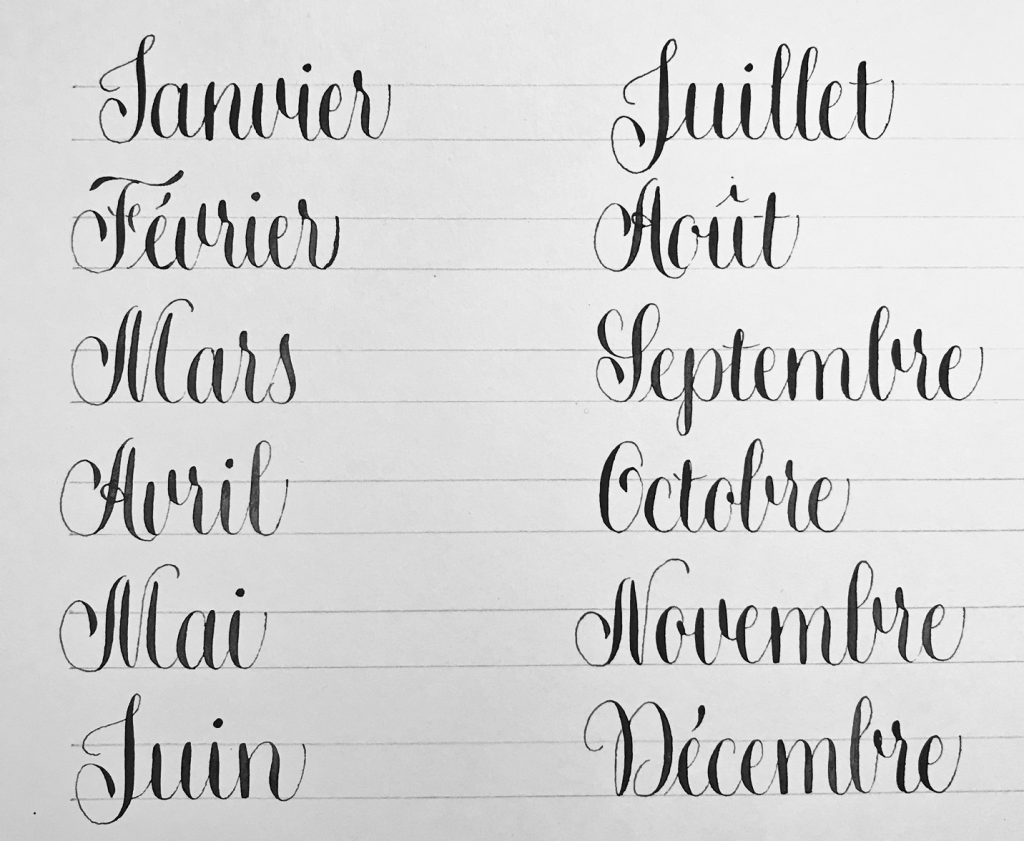
Peut-on écrire à la plume dans un Bujo ?
J’ai auparavant testé que l’écriture à la plume passait bien sur le papier de mon Bujo. En écrivant à la gouache, pas de souci : ça ne fuse pas et ne traverse pas les pages. J’ai un carnet Leuchturm, mais j’ai essayé aussi sur des carnets Hema ou Muji et je n’ai pas eu de problèmes.
Simplicité et sobriété
J’ai essayé de travailler sur quelque chose de simple, épuré, graphique, féminin et rapide à faire.
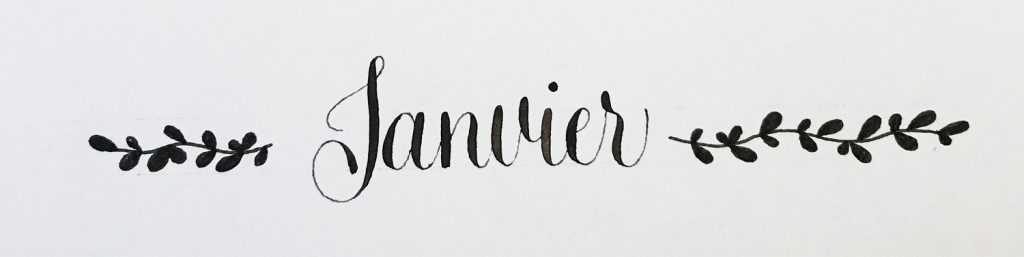
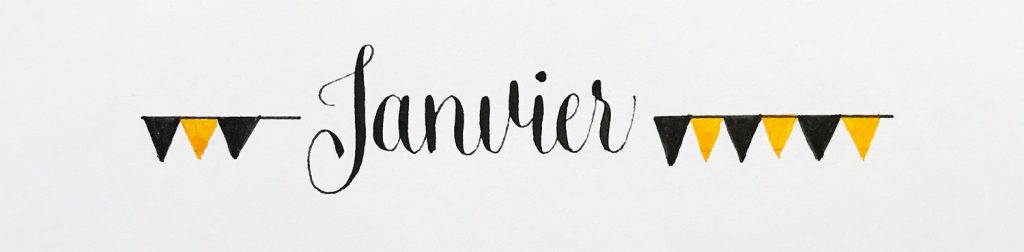
L’idée était aussi d’exploiter des formats un peu « étiquette ».
Au final, j’ai choisi pour janvier, mais j’ai déjà des pistes sympas pour les autres mois de l’année.
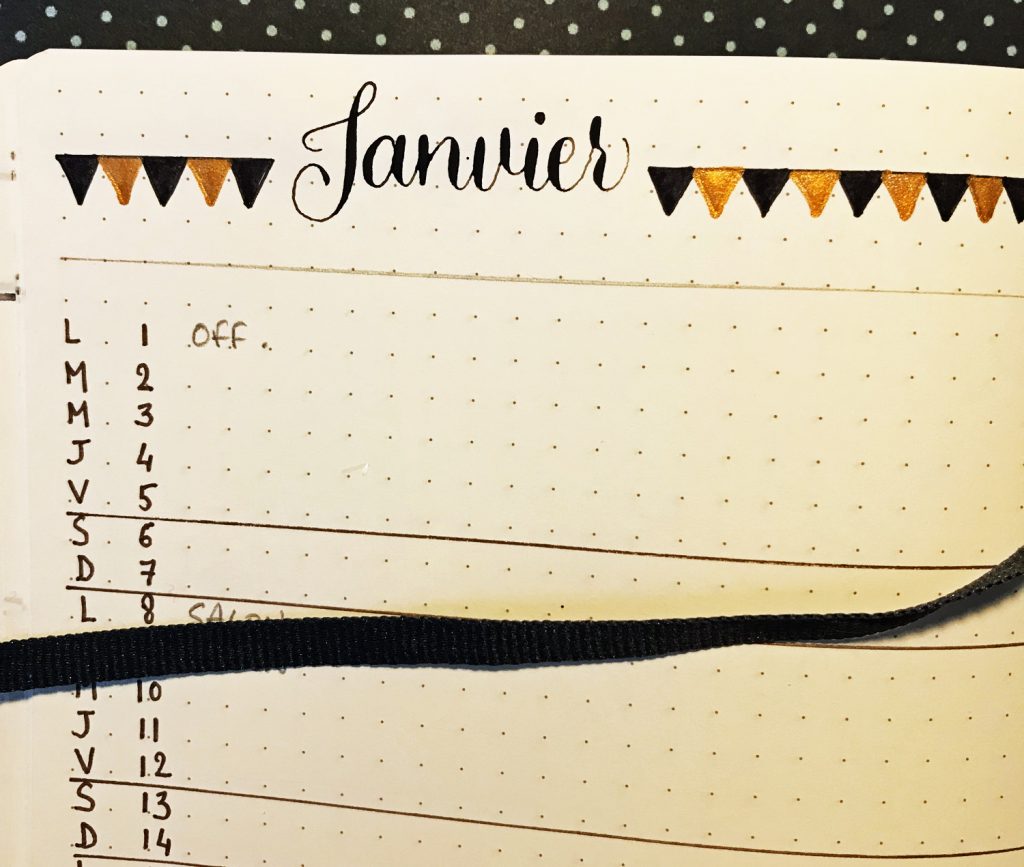
Ces petites compositions simples peuvent aussi servir dans d’autres contextes : étiquettes, cartons de table, etc…
Bonjour! Merci pour cet article qui donne des idées ! J’aime énormément les fleurs autour du janvier. Saurais-tu le nom de la police utilisée pour les deux dernier janvier, ou une qui ressemble ? J’aimerais essayer de faire les autres mois dans ce style là. Merci d’avance et bonne journée 🙂
Bonjour Margot, heureuse que cet article t’inspire. Je n’utilise pas de « polices », les textes sont écrits à la plume pointue. C’est une capitale toute simple, allongée en hauteur. L’effet fin/gras est dû à la plume. Bon courage pour tes créations.